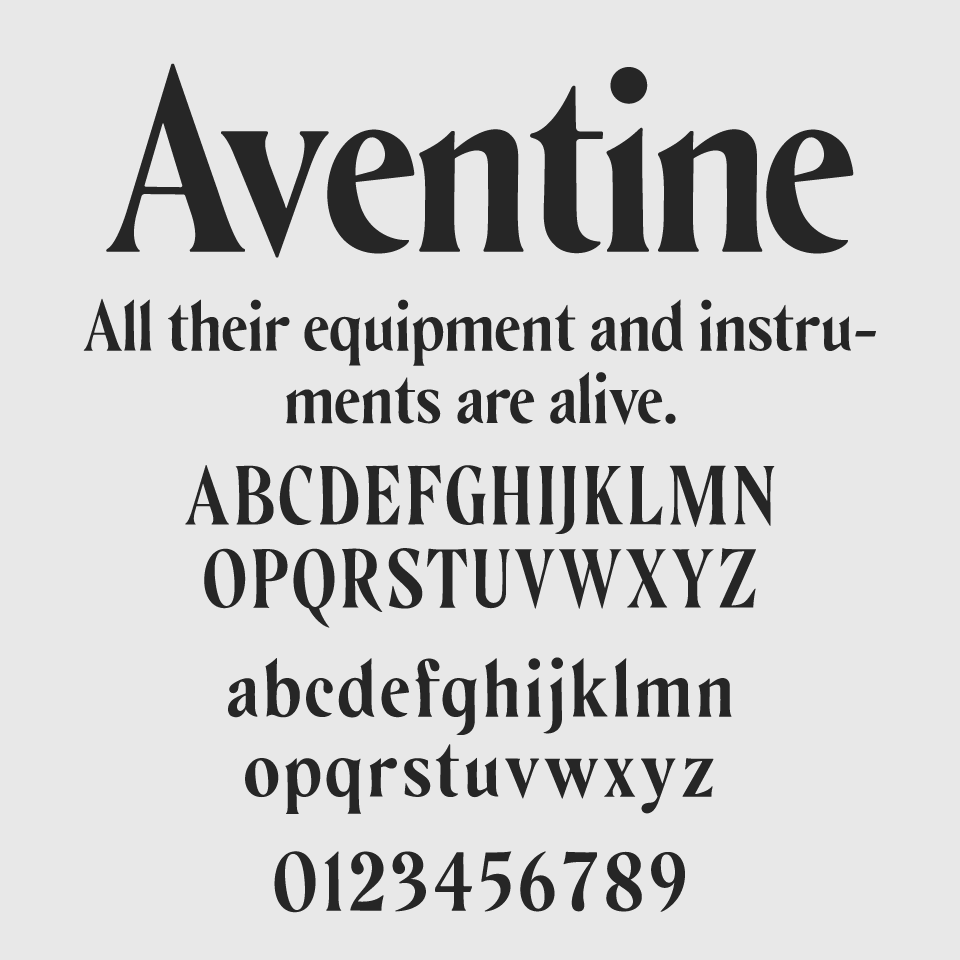
Aventineフォントは、クラシカルな書体にほんの少しのモダンなひねりを加えた、落ち着きのあるセリフ体フォントです。
縦のラインはやや太く、横線は細くメリハリが効いており、文字に品格と重みが感じられるフォントです。少し鋭角なカーブが特徴で、ちょっと硬質な中にも優雅さが潜んでいる素敵なデザインです。
全体的に歴史ある書籍や彫刻碑文を彷彿とさせるような佇まいで、格式の高さや洗練された雰囲気を表現する場面にぴったりです。印象は端正ながらも堅苦しさはなく、コンテンポラリーなデザインとの相性も良好です。タイトルやロゴ、パッケージなどに品格を添えたいときに使いたいフォントです。